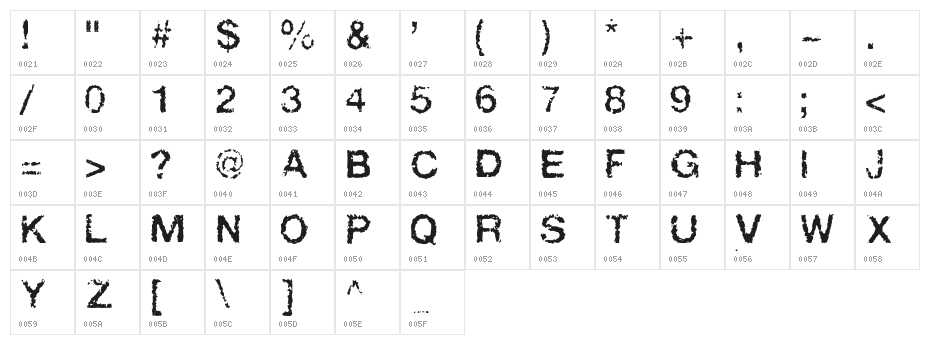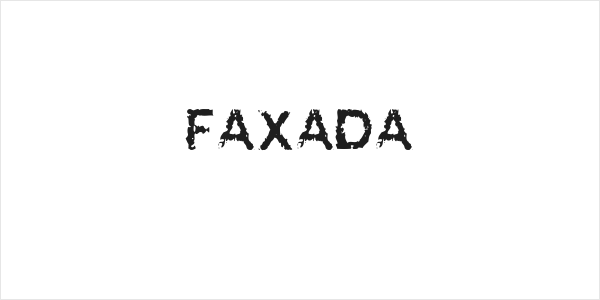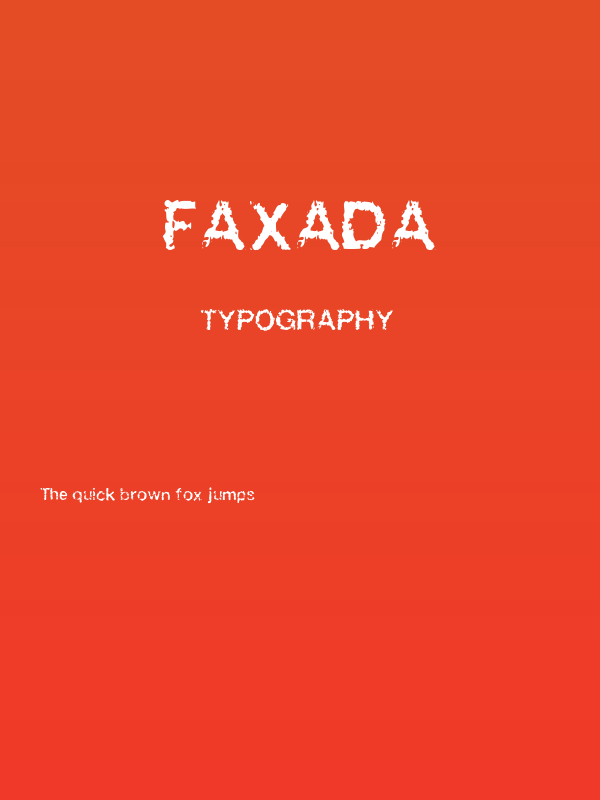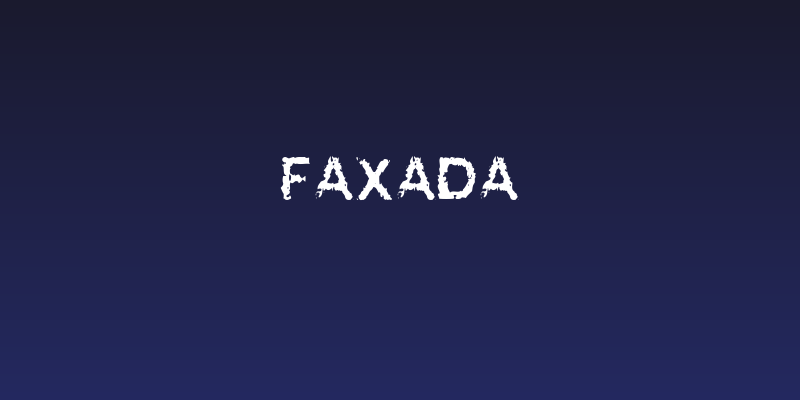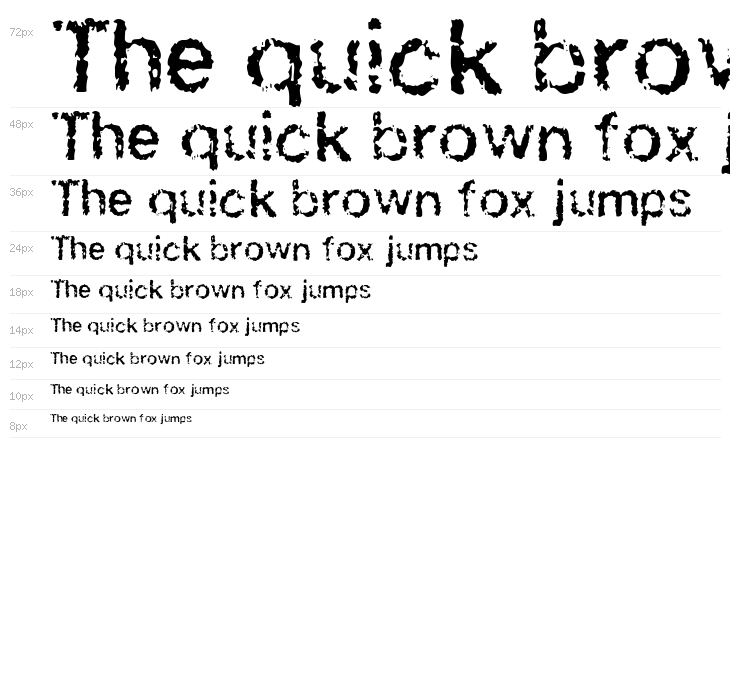
FAXADA Font
| Categorie | Distorted Eroded |
| Stile generale | Grunge, Distressed |
| Progetti proposti | Ideal for projects that require a gritty, urban feel such as music album covers, posters, or branding for edgy, alternative brands. |